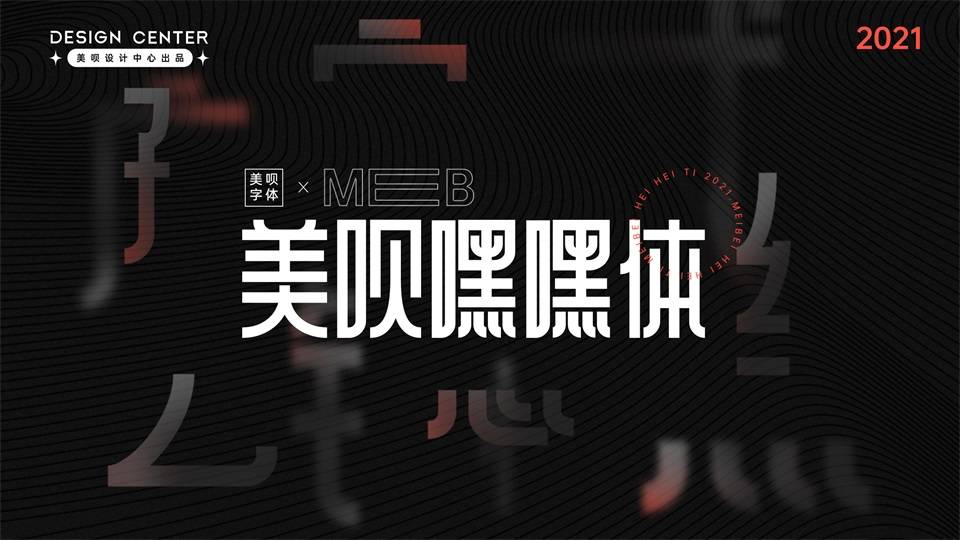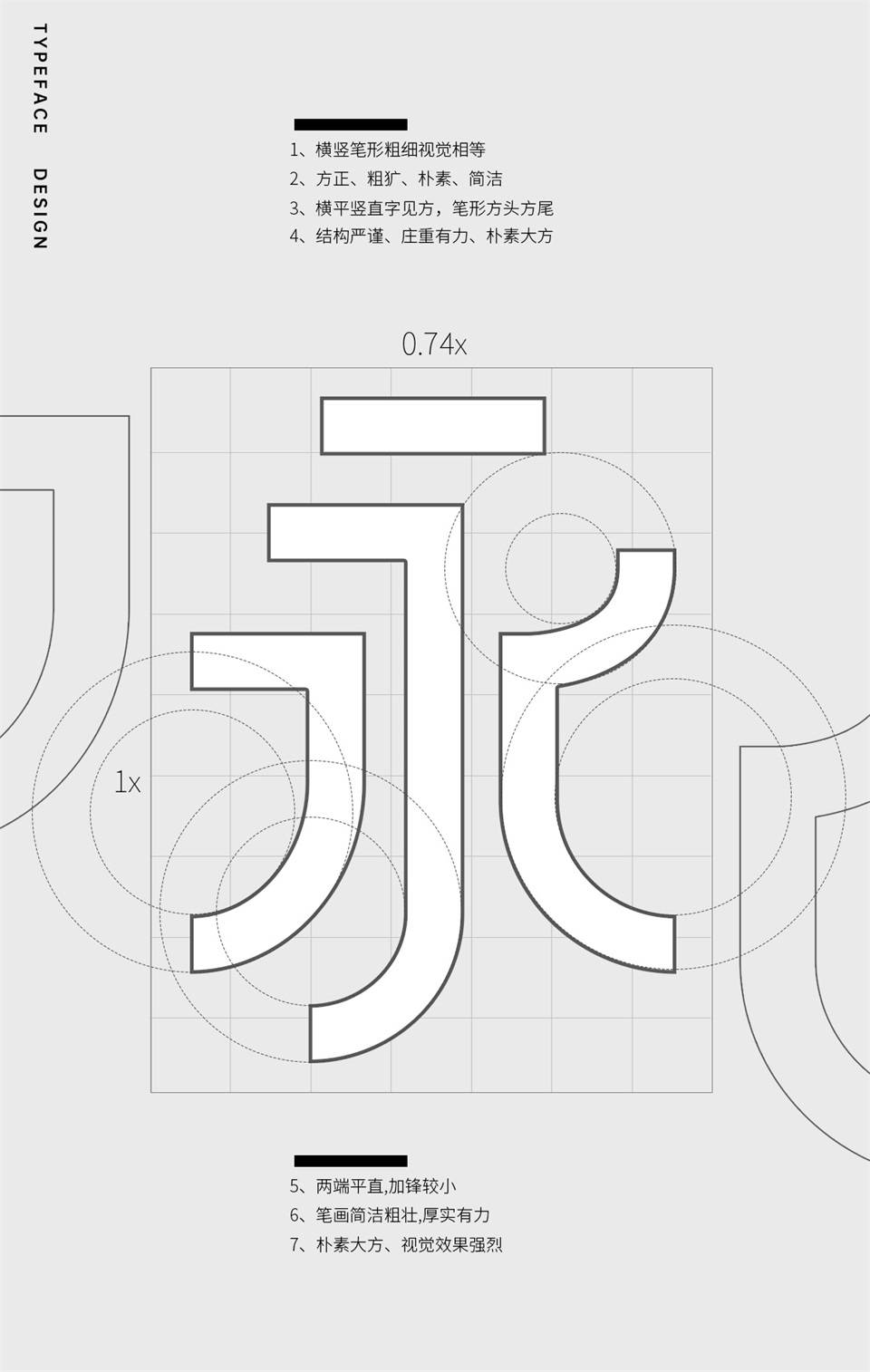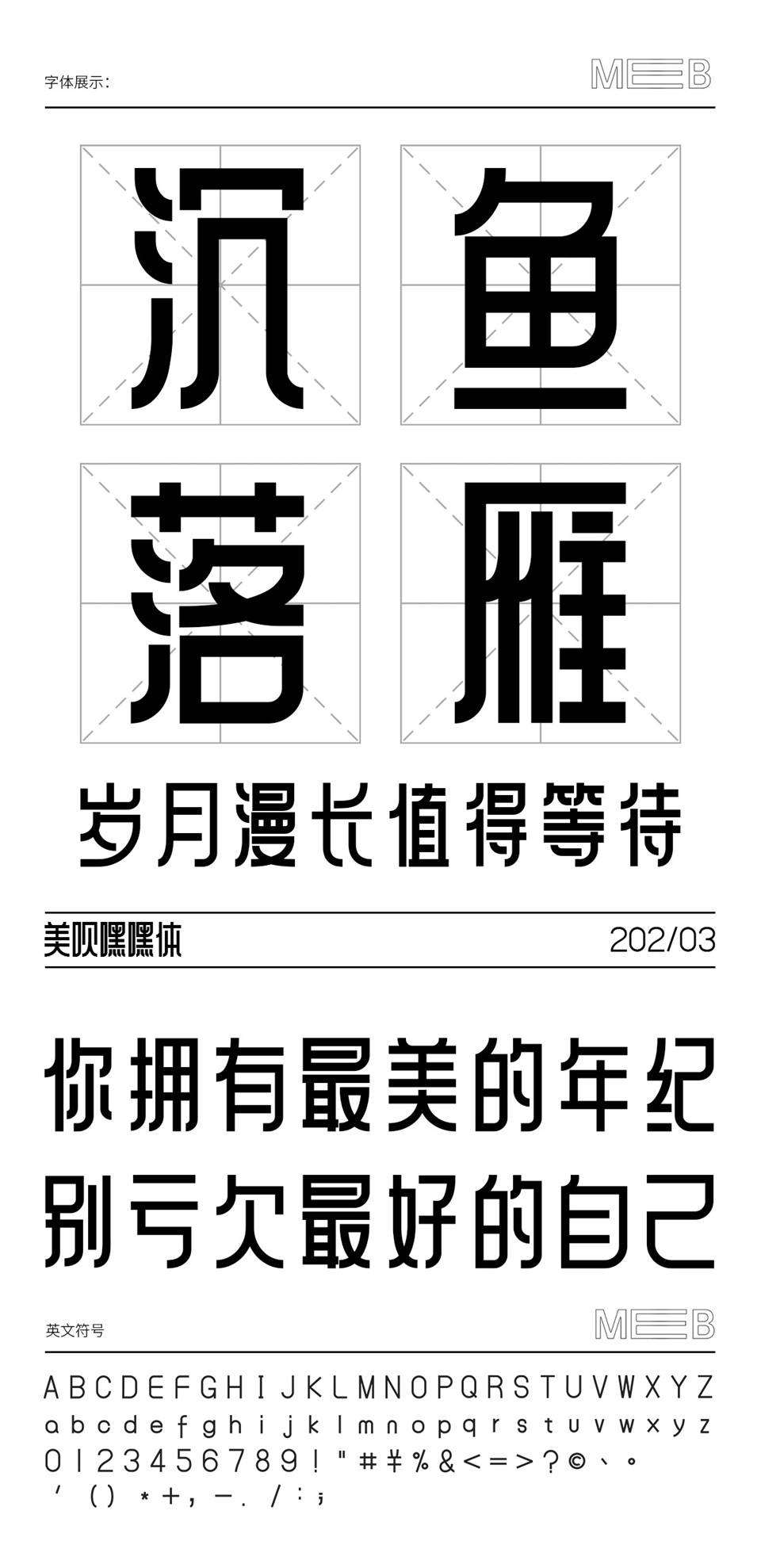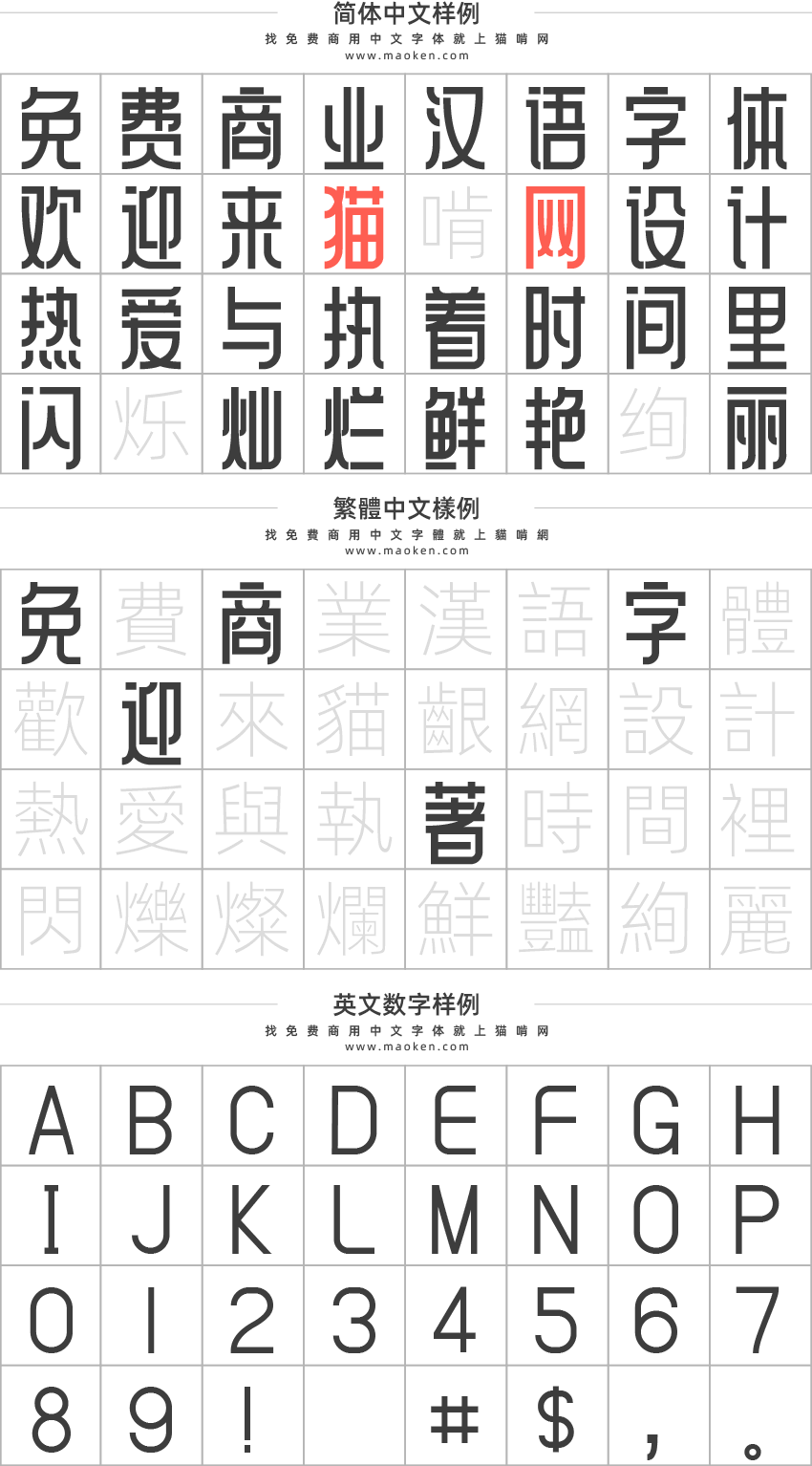
| 字体作者:美呗设计中心 (中国大陆) | 字体字重:1个 |
2021年11月1日,由美呗设计中心出品的首款免费商用字体【美呗嘿嘿体】试用版上线,包含2500+个汉字。
2022年末正式推出【美呗嘿嘿体】完整版啦!
●○美呗嘿嘿体,是由美呗设计中心主导设计的一款品牌字体,也是医美行业首款字体。之所以取名美呗嘿嘿体,一是因为这款字体本身属于黑体,二是融入了美呗人“乐观、皮实”的精神,故取名“美呗嘿嘿体”。
咳咳,美呗设计团队为了让品牌符号更加鲜明、让美呗er更有归属感,他们秉承着“开放、合作、创新“公司价值观,就这样开启了一项完全0经验的设计字体的工作!
●○秉承公司文化价值观,设计团队在工作之余从构思到完成,整整花了两年半的时间,精心打磨出了一套符合现代美业的商用字体。
●○在过往的一年中,我们总能在各个地方“邂逅”美呗嘿嘿体,品宣海报、线下广告、活动运营页面…这一切都离不开成千上万设计师朋友和大V的分享。让这款原创字体成为免费商用的网红字体。对此,作为创作者的我们当然是欣喜和自豪的,感谢每一位使用者对美呗嘿嘿体的喜爱和肯定!
●○这一年,我们也没有停滞不前,在大家的反馈和期待声中我们终于完成了美呗嘿嘿体(全字库)的设计!符合GB2312简体中文编码字符标准的品牌字体,包含6767个中文字符和150+西文及数字符号。
●○我们本着“大道至简,大美天成”的设计理念,以极简的笔画形态使字体展现出一种自然美学。
●○在字形设计上,我们采用1:1.4的比例(白银比例),相比西方比较流行的“黄金比例”,在东方更流行“白银比例”,更能体现出低调内敛的东方之美。
●○相较于之前发布的字库,增加了4203个中文字符,做了字体细节的微调,并且优化了西文及数字符号等,完成了我们给自己定的目标——打造一份属于美呗的全字库,也希望带给大家更好的使用体验感。
●○美呗一直在为东方女性提供美学服务,我们深知每一位女性都有其独特的美,并且尊重每一种美。我们将11年深耕东方美学的经验,刻入美呗嘿嘿体的设计中,赋予字体大气的东方韵味和温婉的东方美学,让其不仅仅是一个个单调冰冷的字符,更是美呗对于美的理解和诠释。现在免费供大家使用,也是希望能够以己之美,成人之美。